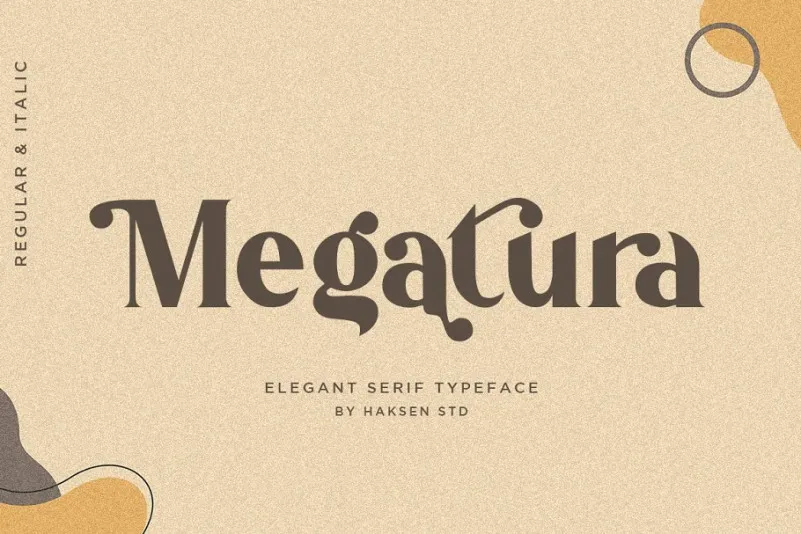
Megatura Sans Serif Font – Fonte Grátis
Megatura Sans Serif Font
A Megatura Sans Serif é uma fonte que oferece um estilo único inspirado na tipografia de artistas talentosos. Ela traz elementos vintage e decorativos ao seu design, mas mantém sua aparência moderna com um poderoso impacto visível. Esta fonte se destaca por suas alternativas estilizadas amplas, permitindo diversas opções criativas para projetos variados. É perfeita tanto para headlines, logomarcas e postais quanto para embalagens de produtos e até mesmo camisetas personalizadas. A Megatura Sans Serif é uma ótima escolha para quem busca um design moderno com uma dose atraente de antiguidade, adequada para múltiplos formatos e aplicações.